植物風の飾り付き数字の描き方
ちょっと特別な数字を描きたいときにぴったり。
植物モチーフの飾りを添えた、おしゃれな数字デザインをご紹介します。
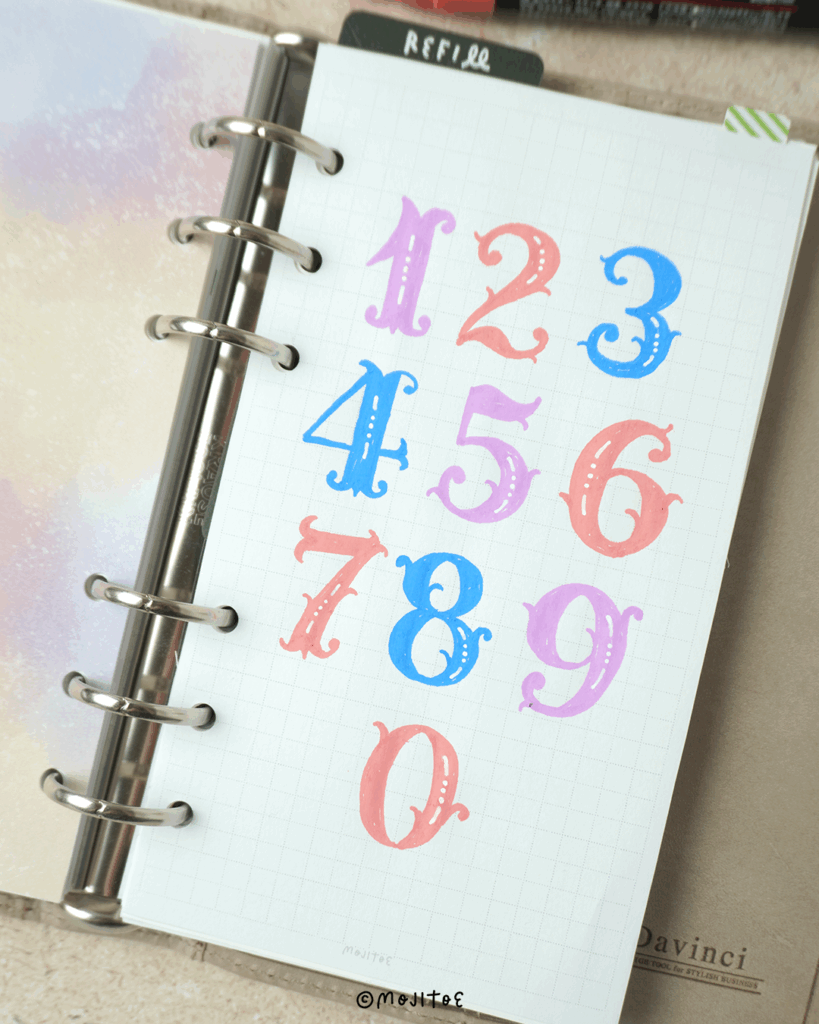
月名やタイトル、ナンバリングなどに、ひと工夫加えたいときにぴったり。
数字にちょっとしたアレンジを加えるだけで、グッと目を引くデザインになります。
数字の一部をクルッと丸めたり、葉っぱのようなモチーフをちょこんと添えたりすることで、さりげなく個性をプラスできます。
描き方ステップ
数字のベースを書き、一部を太くして仕上げていきます。
線の端をくるんと丸めるのがポイント。端がない数字は、ランダムに葉っぱのようなモチーフを足してみましょう。
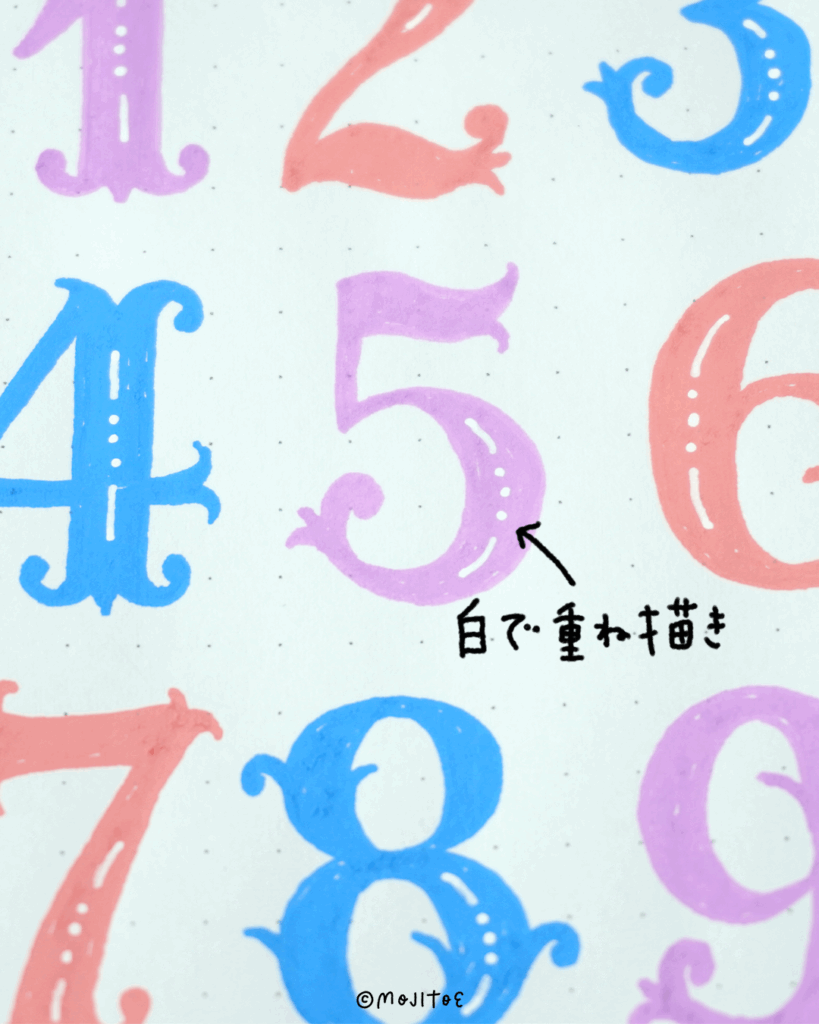
太くした部分に白ペンでドットと線を重ねてアレンジ。
不透明インクのペンがあると便利です。
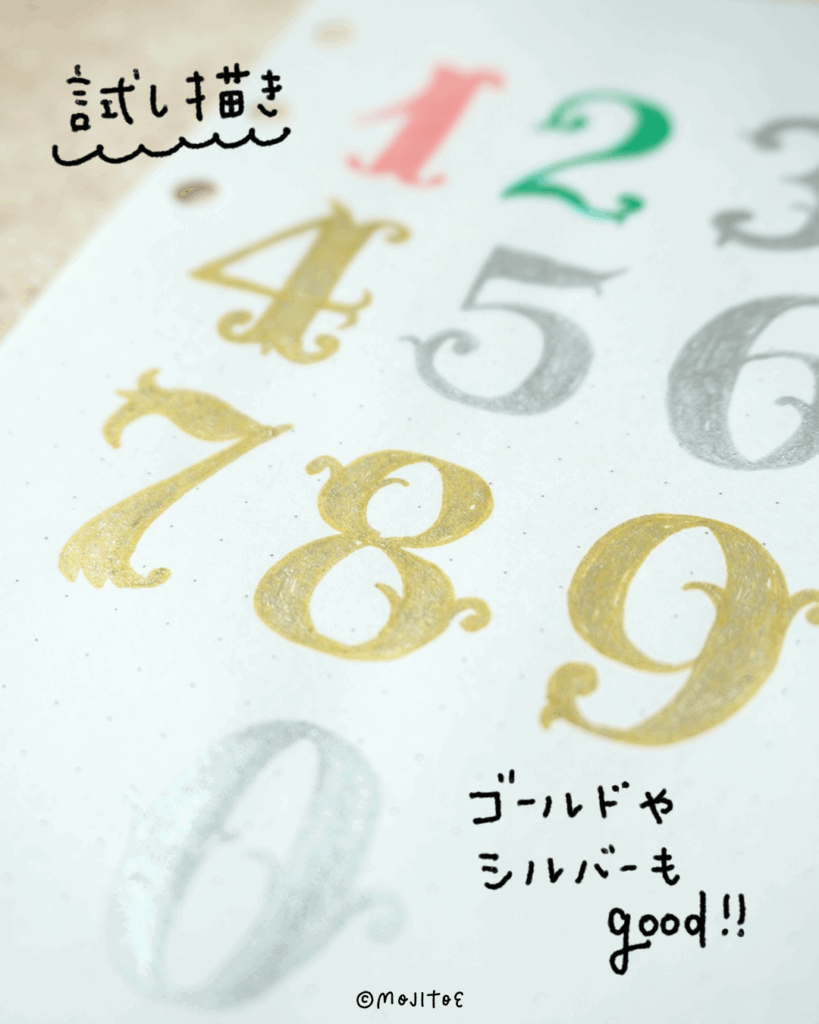
試し書きの際、ゴールドやシルバーも使ってみました。ゴージャス感あって良いですね♪
色んな色で楽しんでみてくださいね。
数字にそっと植物のエッセンスを加えるだけで、日々の記録がほんの少し特別になります。
手帳やカードづくりに、ぜひ取り入れてみてくださいね。